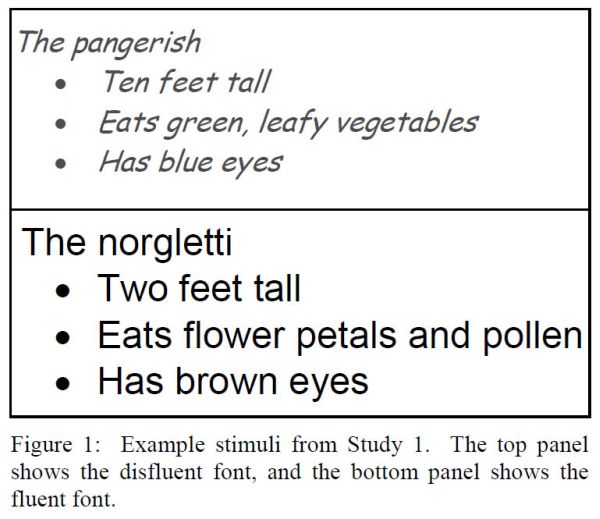
Alien Test - Arial VS Comic Sans
* An extract from the Princeton University test
* The text at the top is in Arial; the bottom is in Comic Sans MS
* Volunteers were able to remember more when the information was written in the bottom font, or in the Bodoni MT font
Ist das wirklich Arial? Sieht eher Richtung Myriad / Frutiger / etc. aus.
Also nicht dass ich BBC anzweifle, aber dann stimmt wohl was mit meinen Augen nicht. :)
Dass das keine Arial ist sieht man schon aus der Ferne. Princeton hat mehrere solche zweifelhaften Tests mit Font veranstaltet. Peinlich.
Eine solche Aussage möchte ich jetzt erstmal dringend belegt haben. Wie ist z.B. genau die Referenz für den genannten Artikel? Im Journal Cognition finde ich jedenfalls nichts unter den Stichworten »Arial« oder »Comic Sans« (jedenfalls nichts was dem beschriebenen Artikel entspricht; ich muß allerdings morgen noch mal schauen wenn ich Volltextzugriff habe). Unter »Font« findet sich der erste Artikel 2008. Wo ist also genau dieser Artikel? Es ist schon etwas peinlich, daß dieser Artikel im BBC-Artikel nicht ordentlich referenziert worden ist. Erinnert mich irgendwie ganz stark an diese Glosse. :twisted:
Also: wer findet mir die Original-Referenz? Ich krame dann morgen das paper heraus und sehe mal nach, was genau da gemacht wurde und woran die Forscher wirklich interessiert gewesen sind. :tutor:
Beispielsweise jene Späße meine ich.
Auch da muß man sich aber ja erstmal die Primärliteratur ansehen. Von der Internetseite des Herrn gehe ich jetzt mal davon aus, daß der zitierte Artikel der folgende ist:
Oppenheimer, D.M., Leboeuf, R.A., & Brewer, N.T. (in press). Anchors Aweigh: Investigations in cross-modality anchoring. Cognition.
Das ist jedenfalls der einzige Artikel, der in Cognition erscheinen wird. Der Titel sagt schon, daß die Studie mit großer Wahrscheinlichkeit nicht an Comic Sans oder Arial interessiert ist. Solange ich das Paper nicht gesehen habe glaube ich der BBC-Nachricht nicht ein einziges Wort! :tutor:
Ich auch nicht, darauf bezog sich mein "Peinlich." ja.
2008 erschienen ist (siehe auch hier). die seite, von der du die angabe hast, ist nicht aktuell.
die untersuchung, auf die sich der artikel bezieht, ist wohl die hier genannte:
Diemand-Yauman, C., Oppenheimer, D.M., & Vaughan, E.B. (in press). Fortune Favors the Bold (and the Italicized): Effects of Disfluency on Retention. Cognition.
eine kurzversion aus den akten der CogSci-konferenz ist hier verfügbar. nach ?üchtiger durchsicht würde ich sagen, dass der bbc-artikel zumindest die kurzversion des texts weitgehend zutreffend wiedergibt – aber ich bin ja auch kein psychologe.
vielen Dank fürs nachschlagen. Das ist in jedem Fall sehr informativ: Wenn ich mich nicht sehr irre, dann ist das Beispiel in der von Dir zitierten Kurzversion ganz korrekt in Arial und Comic Sans. Man muß da jetzt auf den Artikel warten, ich gehe aber einfach mal davon aus, daß der Fehler hier bei der BBC und nicht bei den Autoren liegt.
Dann ist die ganze Studie aber m.E. großer Mist. Schaut Euch doch das gegebene Beispiel mal an:
Die Größe des angeblich lesbaren Fonts ist mit 16 pt deutlich über der Lesegröße, während man heutzutage an 12 pt Comic Sans ja schon beinahe gewöhnt ist. Der Zeilenabstand ist doch bestimmt auf »einfach« gestellt, das funktioniert mit der Arial nie und nimmer, auch wenn es jeder macht! Das ist viel zu eng. Und jeder, der mal Tschichold gelesen hat, weiß, daß zumindest dieser den Kontrast von schwarzer Schrift auf hochweißem Papier verteufelt. Im Vergleich finde ich persönlich ja den reduzierten Kontrast im oberen Beispiel als sehr wohltuend.
Wenn das wirklich eine anständige Repräsentation dessen ist, was die Herren da gemacht haben, dann nehme ich meinen obigen Kommentar zurück, behaupte das Gegenteil und stimme Bertel damit voll zu: Blanker Unfug, der da verzapft wird! :twisted:
Oder, jetzt mal umgekehrt: wenn das angeblich schlechter zu lesende Beispiel tatsächlich zu einer besseren Aufnahmefähigkeit bei Probanden geführt hat, dann ist es ja eigentlich ein schöner Positiv-Beweis für guten Satz (»gut« ist hier relativ, beide Beispiele verursachen bei mir Augenkrebs).
Wenn ich irgendwann mal 2 Minuten Zeit haben sollte, E-Maile ich den Herren vielleicht mal. So aus Spaß an der Freude! :wink:
Oder mach halt mal mit bei so einer Studie. Wir brauchen Typografie-fähige Wissenschaftler! :party:
Diese wissenschaftlichen Studien zu Schrift und Lesbarkeit sind doch fast immer Murks. Da werden die Schriften praktisch immer auf gleicher Kegelhöhe gesetzt, um sie vegleichbar darzustellen (haha!), oder es wird am Bildschirm eine gehintete 10-Punkt-Arial mit einer PostScript-Poster-Bodoni verglichen und ähnlicher Blödsinn.